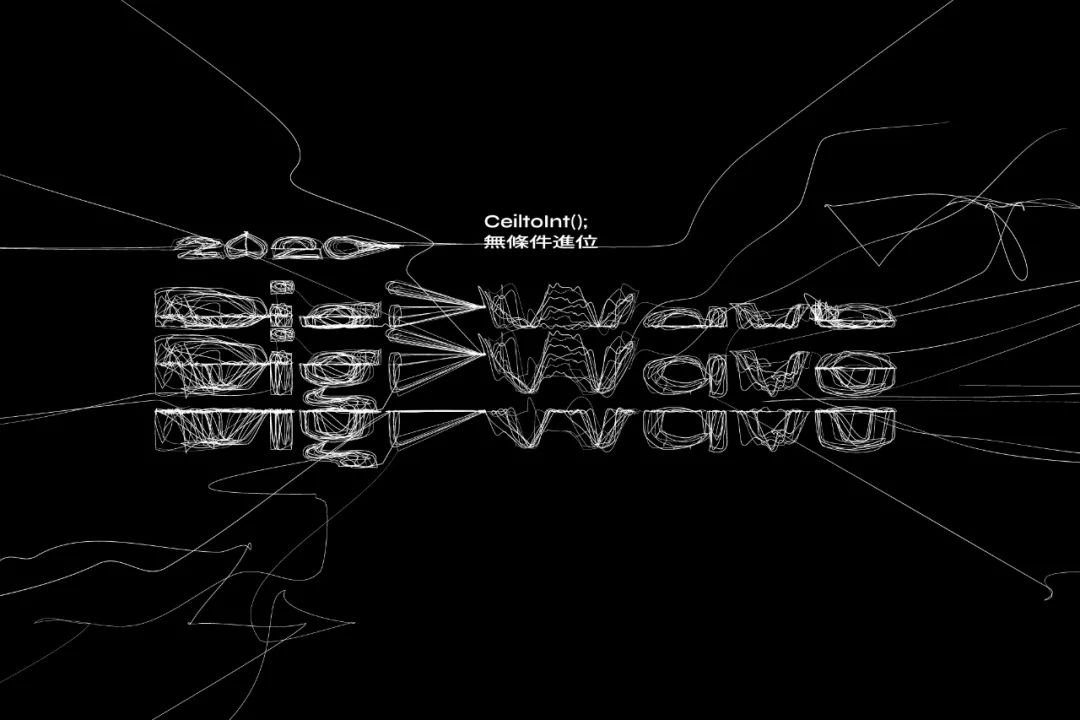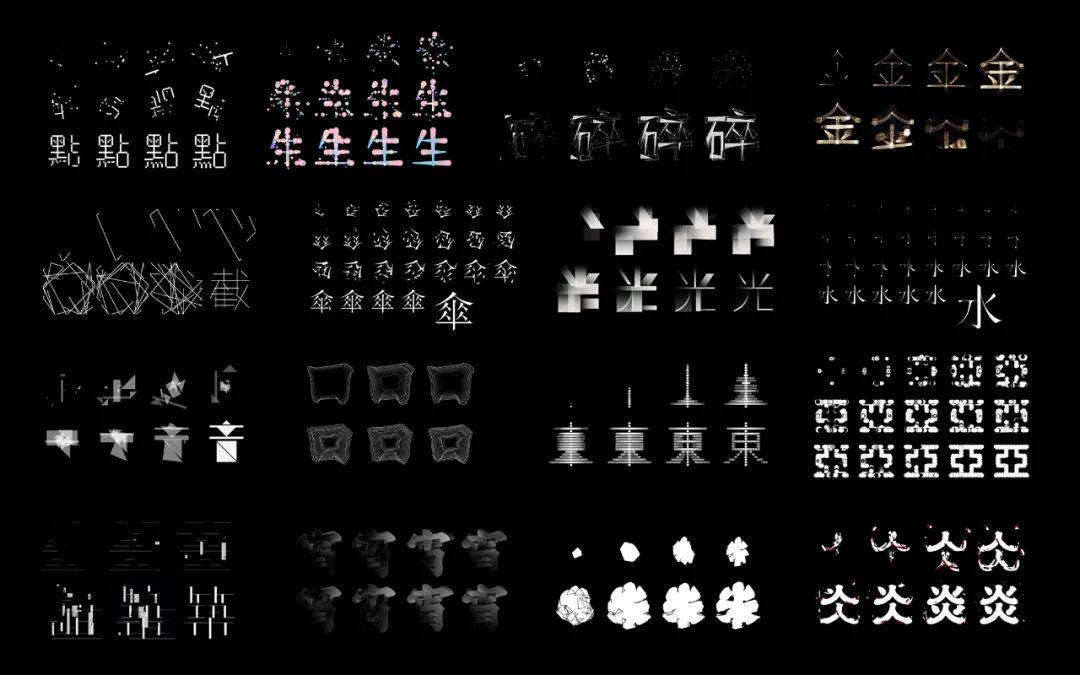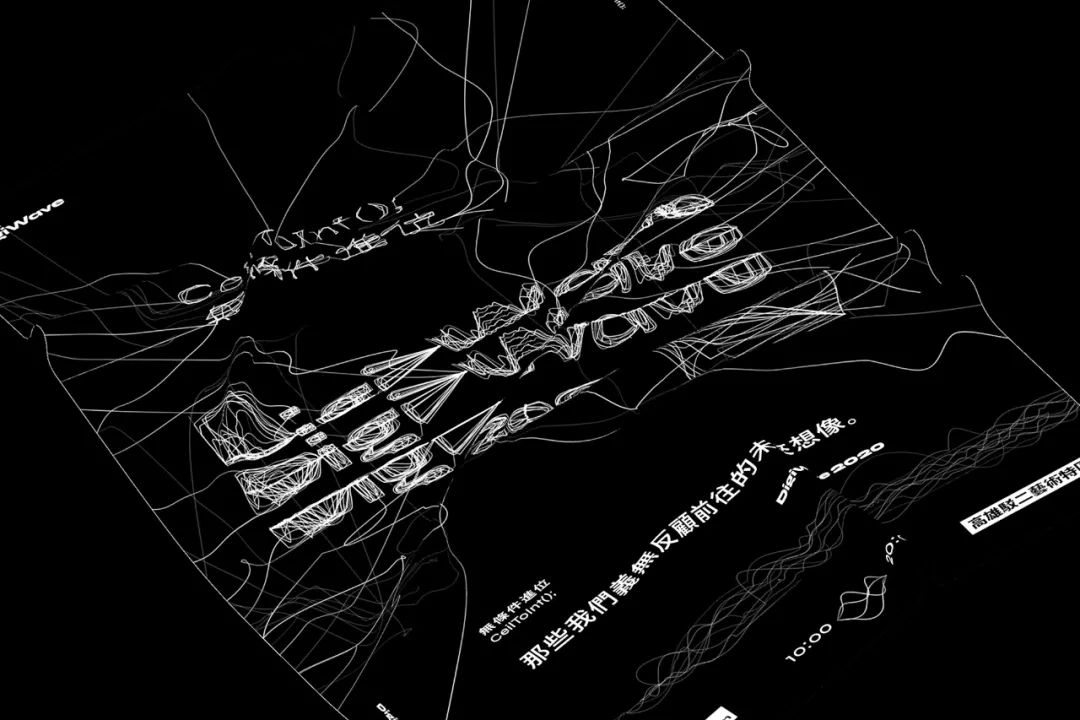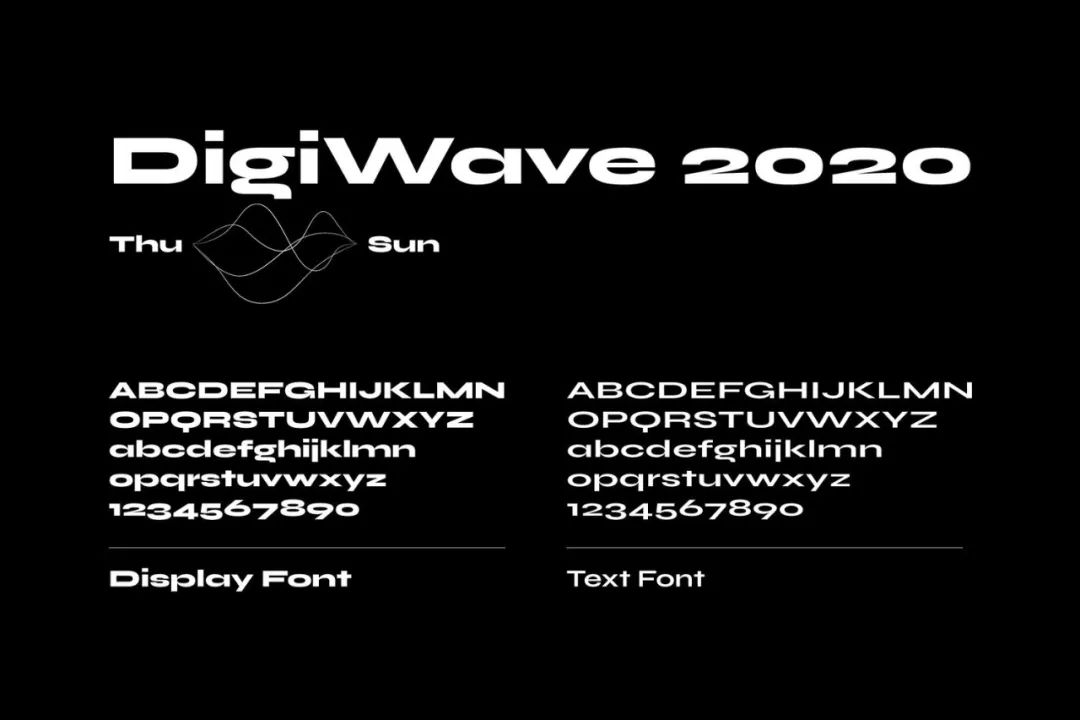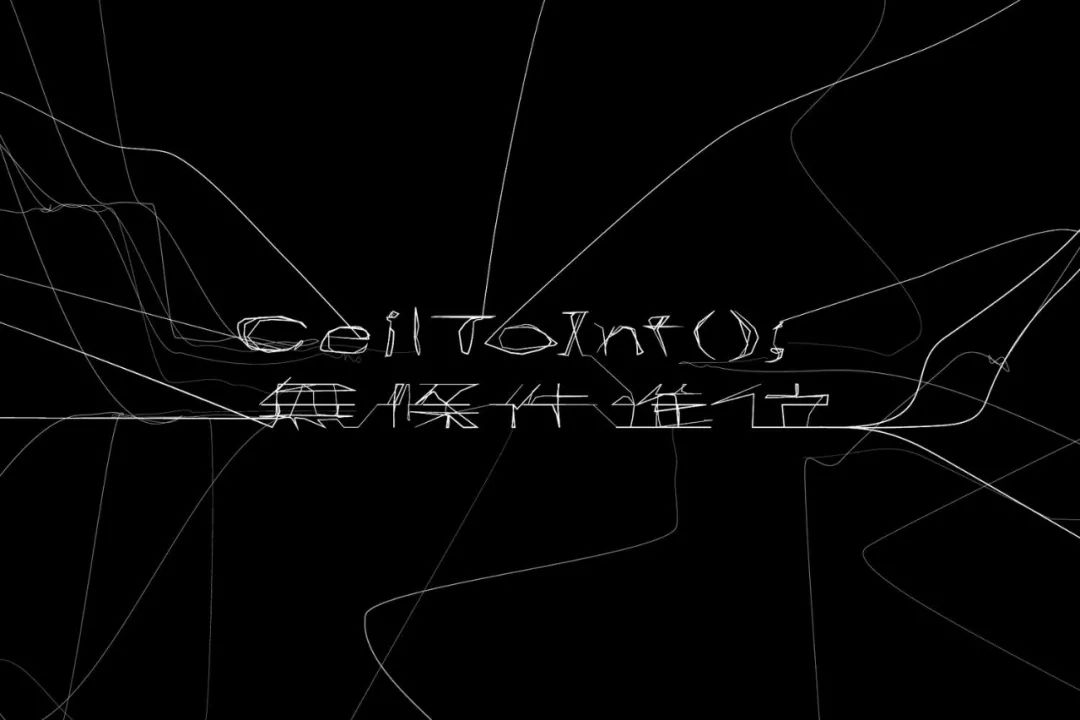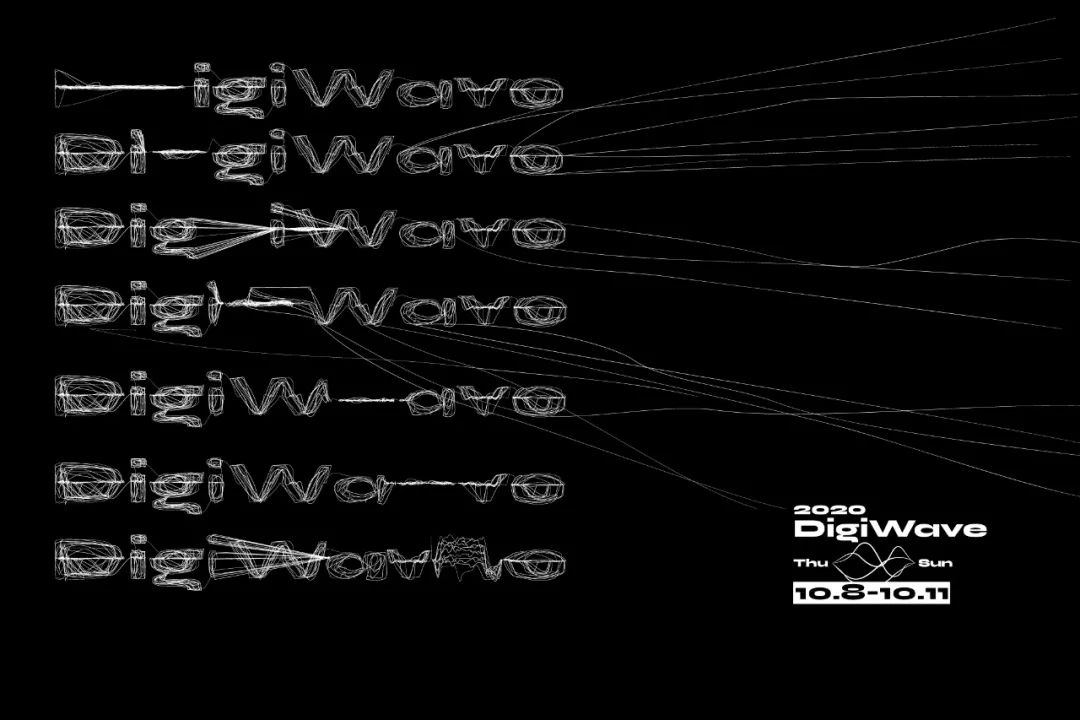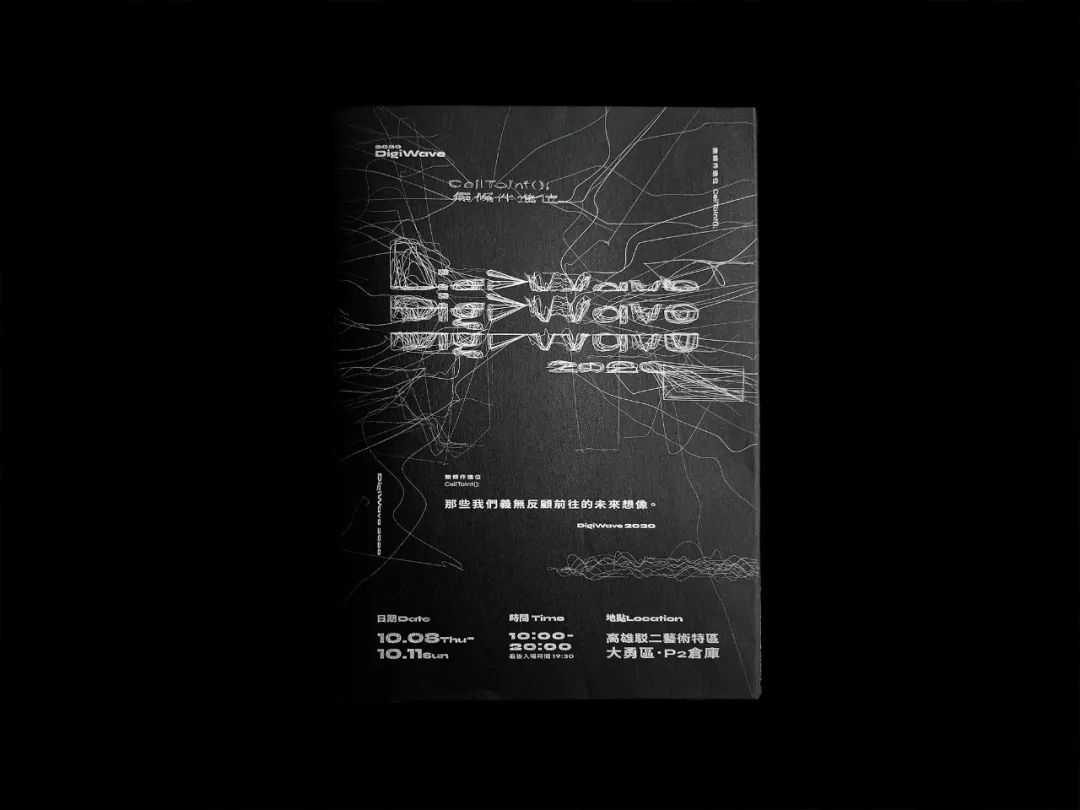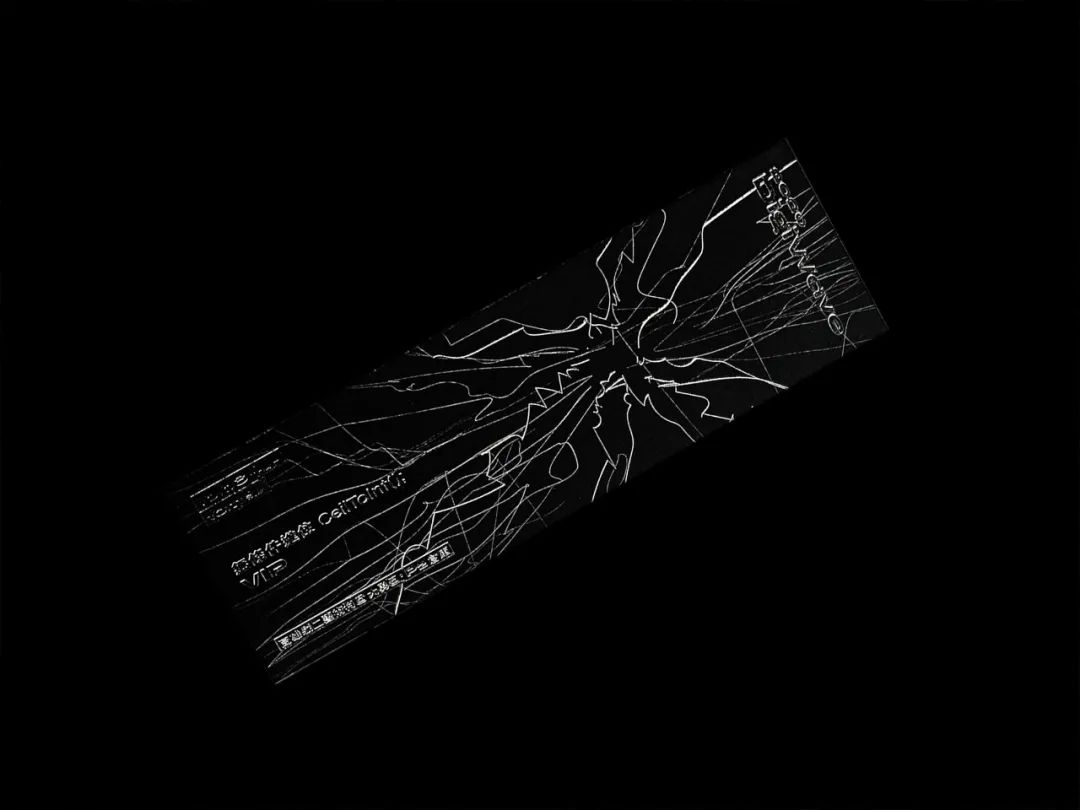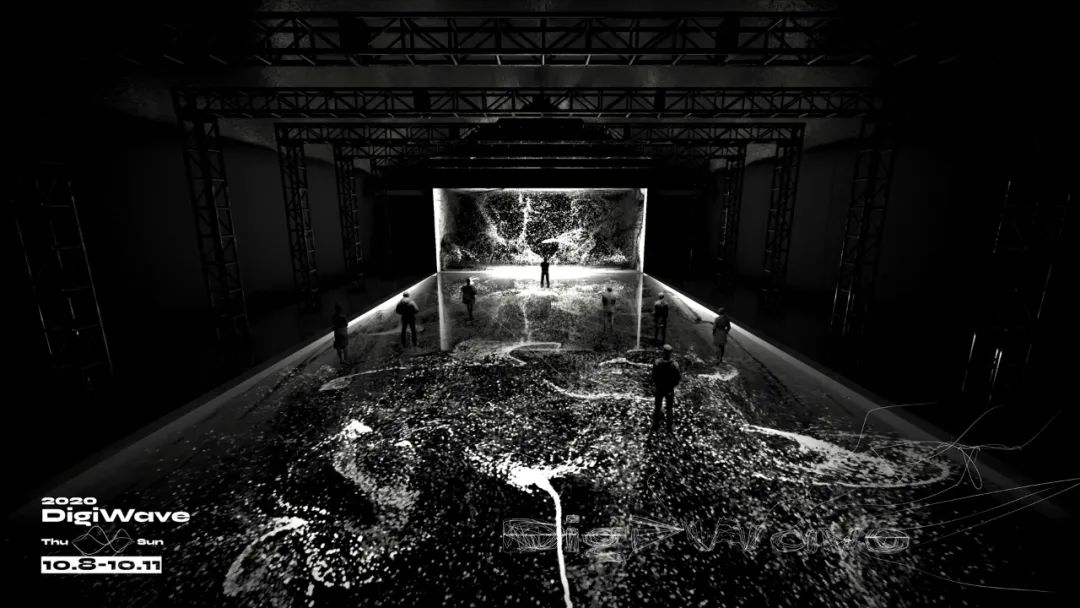
那个做动态字体的何庭安,又出新作了!
为各类品牌提供形象塑造、视觉识别、商业设计及艺术指导工作。这是一个关于将汉字与动态设计接轨的专案。自平面设计进入动态表现以来,动态图像设计(Motion Graphics)始终扮演文化传播以及数位载体中的要角色。而至目前为止多数动态图文案例中,著名案例皆以英文字体作为设计工具,未见特别针对中文动态设计做探讨的相关作品与研究。 中文字体贯古至今,其中流变与种类极其繁杂,数量更以庞然数巨万字计,其中各家设计风格之不同,包含笔画、横竖、撇捺、重心、结构等特性,与拉丁字母便有多处不同,若以欧美设计方法直接套用,则会有 一定程度的抵触之处。要突破此僵局,同时需涉略字体研究、平面设计、动态设计等领域,非一时所能完成;因此本专案开启一系列将中文字体动态化的实验,区分各家字体特性,一步步系统化的整理及发想动态,并藉由巨量的作品展示,以予未来的设计师们参考。前些天,何庭安发布了一个新的设计作品《DigiWave 2020: 無條件進位 CeilToInt();》DigiWave 是一个以「科技」为主轴的庆典,他们们受托为其策划展览内容、形象塑造与视觉设计。他们冀望透过 DigiWave 对「科技带来的影响」的重要议题提出大哉问,不只是之于环境或经济,而是对于人类未来何去何从的终极质问,于是他们拟出了今年的命题:「无条件进位」。若所取位数之右数字非零,则强制进位,不容有他——这种义无反顾,正是他们对于未来的态度。为此,他们打造了一座整合展览、活动、互动的巨大沉浸空间,以电脑演算生成的符码,数位而大器的贯穿整个展览主视觉,将观众毫无保留扔进我们所想像的数位场域之中。
无法辨识机器或人的那一刻、身体可以任意定义的那一刻、无法分辨真实虚拟的那一刻、发现宇宙其他文明的那一刻,我们该如何自处?